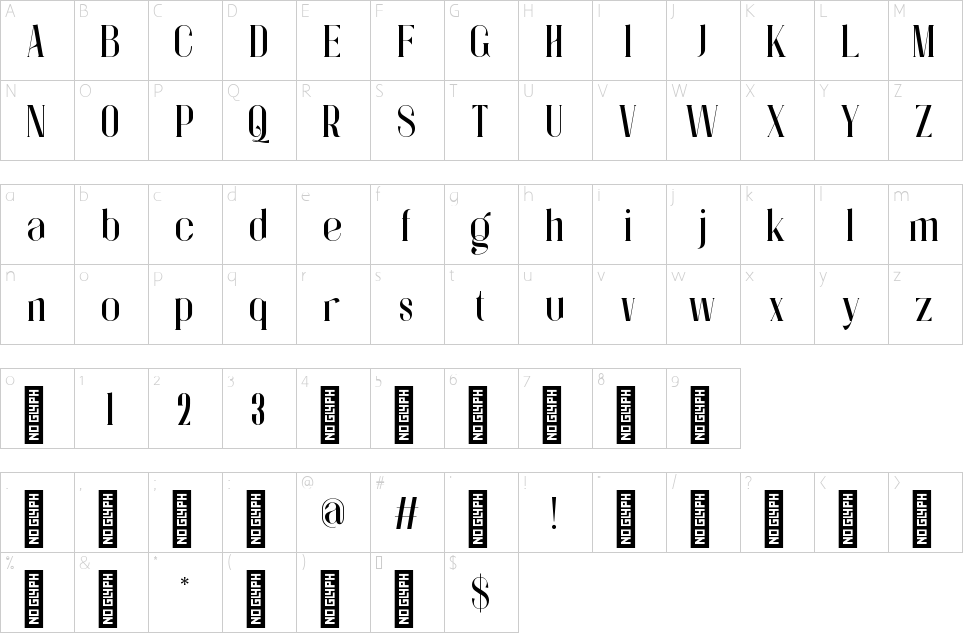
A fonte Arcane Whispers é um charme gráfico que oferece uma experiência única para designers e amantes da arte digital. Desenvolvida por Helotype, essa fonte adquire um toque misterioso e sedutor, ideal para projetos digitais que exigem um toque único. Com seu design elegante e detalhado, Arcane Whispers traz um ar de misticismo a qualquer projeto gráfico, seja ele um brochura de design gráfico, uma capa de livro digital ou até mesmo um poster de arte digital. Com uma baixa quantidade de downloads, Arcane Whispers já conquistou um seguidor fiel, um número que reflete seu valor incomum e sua capacidade de oferecer um toque especial a qualquer projeto. Que tal experimentar uma amostra de seu charme? Descarregue Arcane Whispers e faça sua arte digital brilhar com esse design misterioso e único.